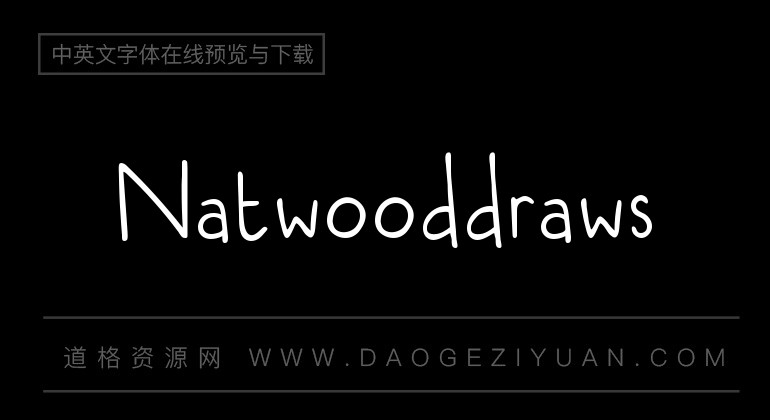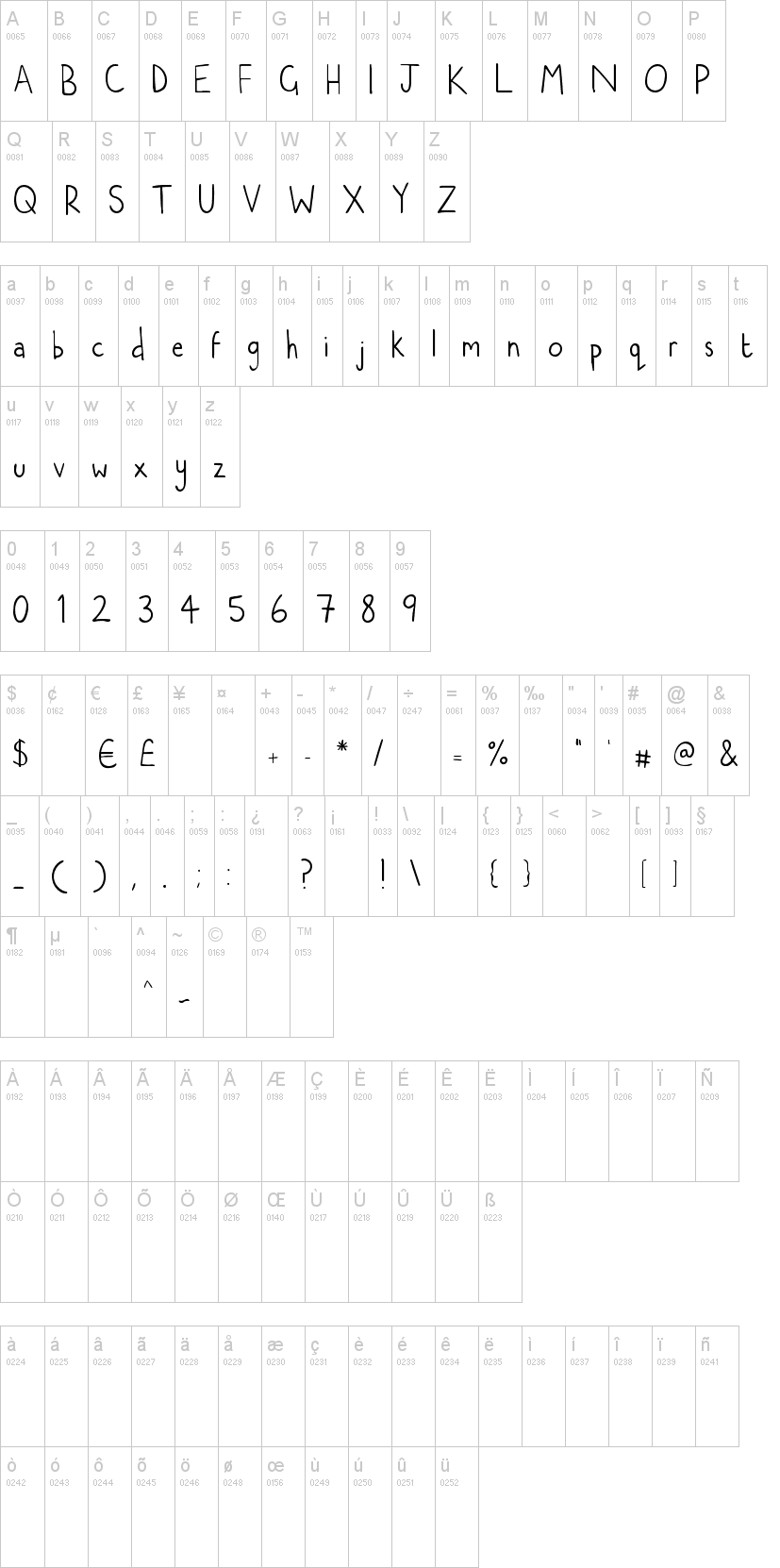
Natwooddraws
? Natwooddraws 字体是一种手写体字体,由英国设计师 Nat Wood 创作。它具有轻松、活泼、友好的特点,拥有稳重的笔画和温暖的氛围,可以提供给你一种温柔而清新的设计风格。它的字符具有细节,可以提供给你更多的选择。它的字体可以用于印刷、网页和数字媒体,适合用于标题、标签、标语等。
Natwooddraws是一款非常不错的手写艺术字体,具有很好的视觉感,适合于文化类的宣传设计、商业类品牌的广告和产品包装设计以及个性化文字排版等较多场景。